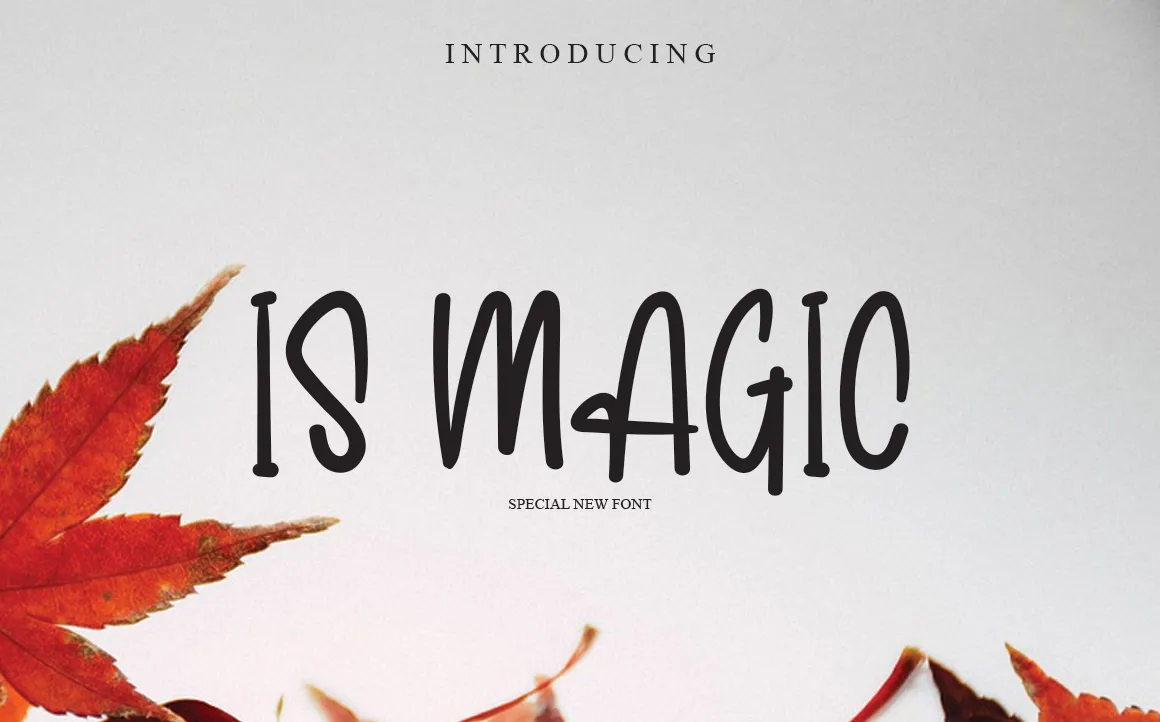
Is Magic Font – Download Grátis
Is Magic Font é uma fonte script única e encantadora, projetada para inspirar criatividade com sua elegância descontraída. Seja para adicionar um toque pessoal à sua próxima postagem no Instagram ou se você está buscando a perfeita chamada gráfica para um projeto de DIY, Is Magic Font tem o potencial de transformar qualquer ideia original em uma verdadeira obra de arte. Este é um recurso valioso para designers e criadores que desejam dar vida aos seus projetos através do texto, oferecendo uma opção fácil e divertida para adicionar um toque especial a qualquer projeto visual.